今回は、Steven Heller、Louise Fili 著の『Scripts: Elegant Lettering from Design’s Golden Age』を紹介します。
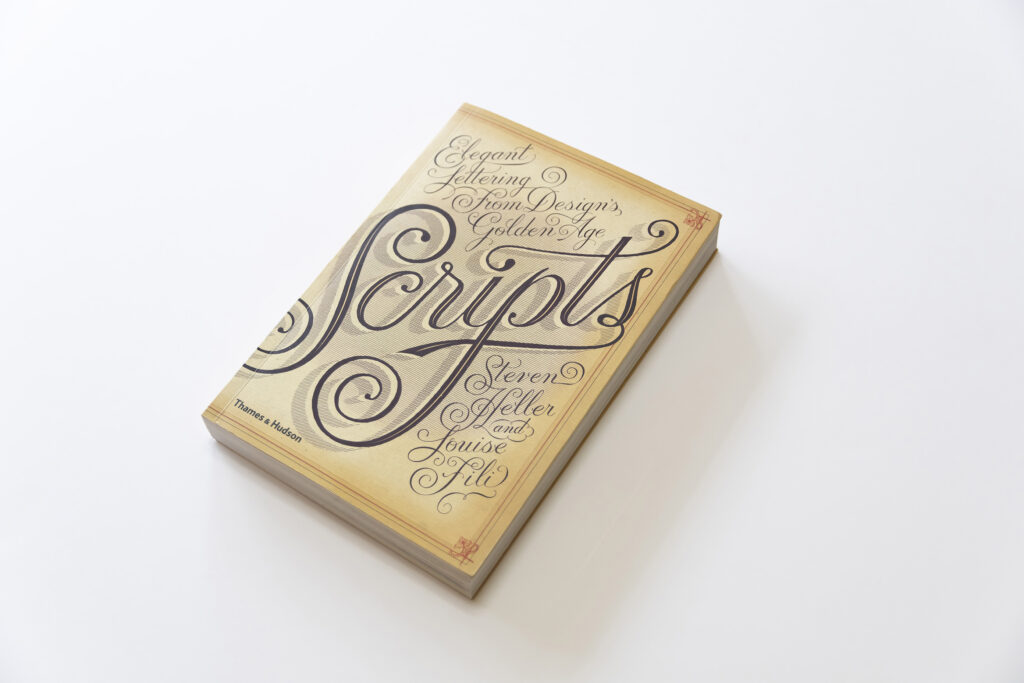
欧文の筆記体(スクリプト体)の全盛期である19-20世紀のヨーロッパ、アメリカで描かれたスクリプト体を集めたビジュアルブック。看板やパッケージなどのレタリングから、活字書体の見本帳の一部まで、様々な様式の美しいスクリプト体をフルカラーで堪能できる見応えのある一冊です。
筆記体は使用する筆記具や筆法によって表情豊かな形を描画することができるので、個人的には書体デザインをする上でのインスピレーションの宝庫だと思っています。スクリプト系の書体はもちろん、その他のスタイルの書体をデザインする時にもこの本をはじめ色々な筆記体に触れると良い刺激になりアイデア出しが捗ります。